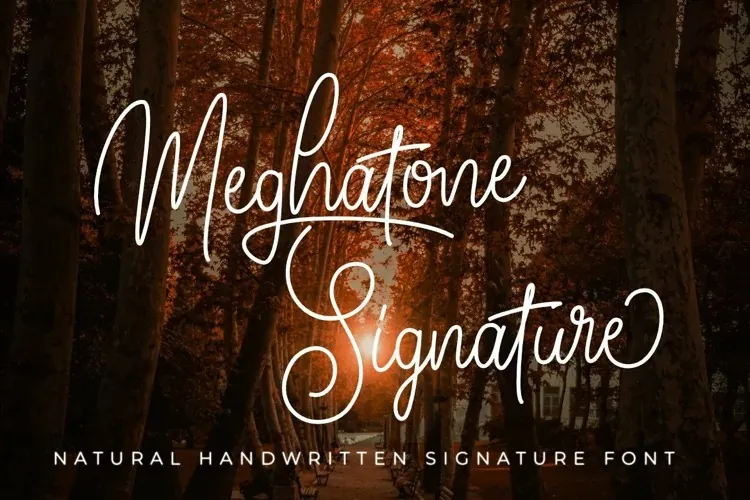
Esta fonte foi criada pela Madatype Studio e é perfeitamente indicada para ser usada como uma assinatura única. Ela possui um estilo natural e elegante, que transmite sofisticação sem perder a personalidade. Com seu traçado fluido e agradável aos olhos, ela é ideal para adicionar uma pitada de toque autoral ao seu design. A Meghatone Signature Font se destaca como fonte perfeita para aqueles desejando um elemento handwritten que seja elegante o suficiente para os ambientes mais formais, mas também casual e versátil para aplicações diários. Com esta fonte em sua disposição, você pode incorporar a personalidade de uma assinatura única no seu trabalho sem sacrificar o profissionalismo necessário.